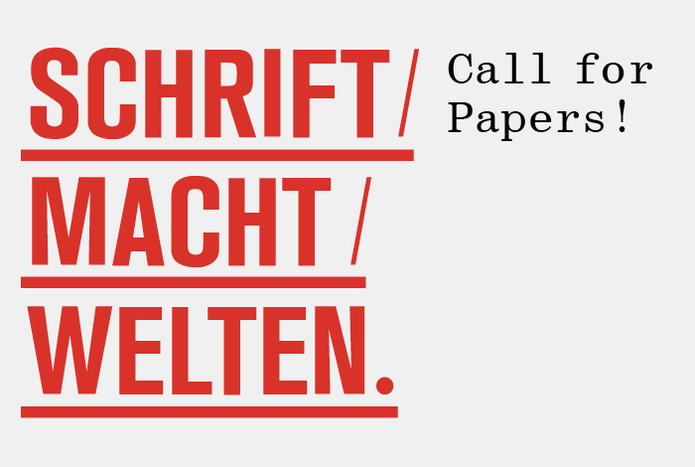
Unter dem Thema Schrift / Macht / Welten – Typografie und Macht fragt die fünfte Jahrestagung der Gesellschaft für Designgeschichte (GfDg) im Rahmen von ON-TYPE und in Kooperation mit dem Studiengang Kommunikationsdesign der FH Mainz am 4. und 5. Mai 2012 nach den politischen Dimensionen von Typografie.
Wie politisch ist Schrift?
Oder: Wer bestimmt die Schrift?
Wie spricht der Staat mit seinen Bürgern?
Oder: Schrift und Gesetz
Welches Corporate für Deutschland?
Oder: Schrift und nationale Identität
Wie kommuniziert die Stadt?
Oder: wandelnd zwischen intelligenten Fassaden und subversiven Icons
Welche Botschaften tragen wir auf der Haut?
Oder: Trends, T-Shirts und Tattoos
Wer führt den Diskurs über Typografie?
Oder: Meinungen und Meinungsmacher
Wer erinnert vergessene Sprachen und Schriftsysteme?
Oder: Schrift und kulturelles Gedächtnis
Wem gehört das digitale Wort?
Oder: Jahrzehnte nach dem propagierten “end of print”
Wie kommuniziert eine globalisierte Welt?
Oder: Schrift in Zeiten von Unicode
Wem gehört die Schrift?
Aus dem Pressetext: »Schrift begegnet uns überall. Beim Lesen eines Zeitungsartikels, eines Romans oder eines Straßenschildes konzentrieren wir uns auf den Inhalt, ohne die Buchstaben und Zeichen bewusst wahrzunehmen. Schrift transportiert in erster Linie Inhalte, Buchstaben sind aber auch visuelle Zeichen. So gehen Typografinnen und Typografen selbstverständlich davon aus, dass die Wahl einer Schrift auch den Charakter eines Textes und damit einen Teil seiner Aussage mit gestaltet.
Der Blick aus der Perspektive der Designgeschichte auf das Phänomen »Typografie und Macht« soll herausstellen, dass unser Umgang mit und unsere Rezeption von Schriften nicht alleine durch die ästhetischen Vorlieben einzelner Gestalterinnen und Gestalter geprägt ist, sondern auch durch schriftpolitische Diskurse. So sind und waren wegweisende gestalterische Haltungen, eingebunden in gesellschaftliche Entwicklungen und Diskussionen, oftmals politisch motiviert – etwa das unbedingte Bekenntnis der gestalterischen Avantgarde zu Groteskschriften und konsequenter Kleinschreibung.
Dass Typografie keinesfalls neutral ist, verdeutlicht vor allem die machtpolitische Instrumentalisierung von Schrift, gerade in Deutschland: Wie ein tiefer Riss zog sich der Streit zwischen Fraktur und Antiqua bis weit ins 20. Jahrhundert, und bekanntlich wurde die Typografie auch von den Nationalsozialisten ideologisch aufgeladen.
Heute manifestiert jede Wortmarke, die durch eine bestimmte Schrift ihren ganz eigenen Charakter erhält, das Wechselspiel zwischen Schrift und Macht, indem bestimmte Schriften unweigerlich die dazugehörigen Imaginationswelten evozieren. Aber auch die Kommunikationsguerilla begreift das Spiel mit großen Schrifttraditionen und/oder Logos als subversiven Kommentar zu Macht und Freiheit.«